Font chữ viết tay (handwriting font) luôn là xu hướng thiết kế được ưa chuộng nhờ vẻ đẹp tự nhiên, mềm mại và cá tính. Trong năm 2024, các font viết tay tiếp tục thống trị trong thiết kế logo, thiệp cưới, quảng cáo và thương hiệu.
Top 10 Font Chữ Viết Tay Đẹp Nhất 2024 Dành Cho Thiết Kế
1. The Seasons – Font Viết Tay Sang Trọng
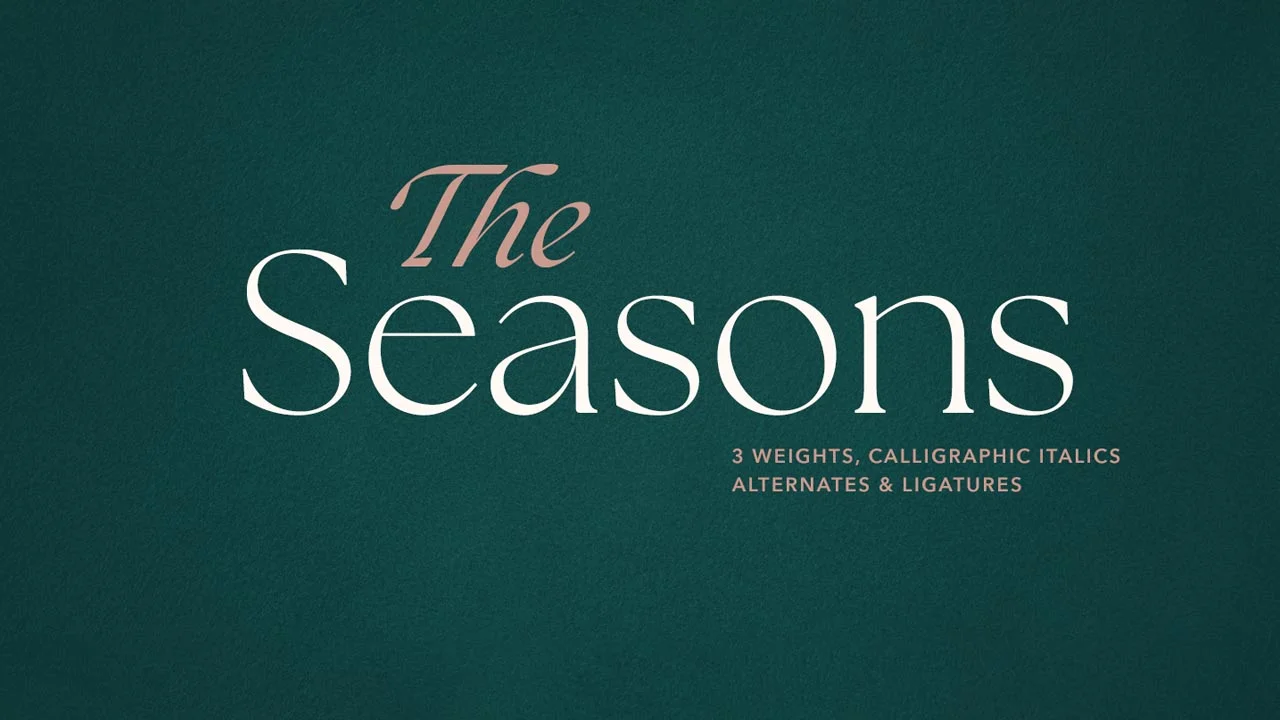
✅ Phù hợp: Thiệp cưới, thương hiệu cao cấp, logo thời trang
✅ Ưu điểm: Nét thanh thoát, uốn lượn tinh tế, mang lại cảm giác quý phái
2. Hello Valentine – Font Lãng Mạn
✅ Phù hợp: Thiết kế Valentine, quảng cáo sản phẩm nữ tính, blog cá nhân
✅ Ưu điểm: Nét mềm mại, chữ nghiêng nhẹ nhàng, tạo cảm giác ngọt ngào
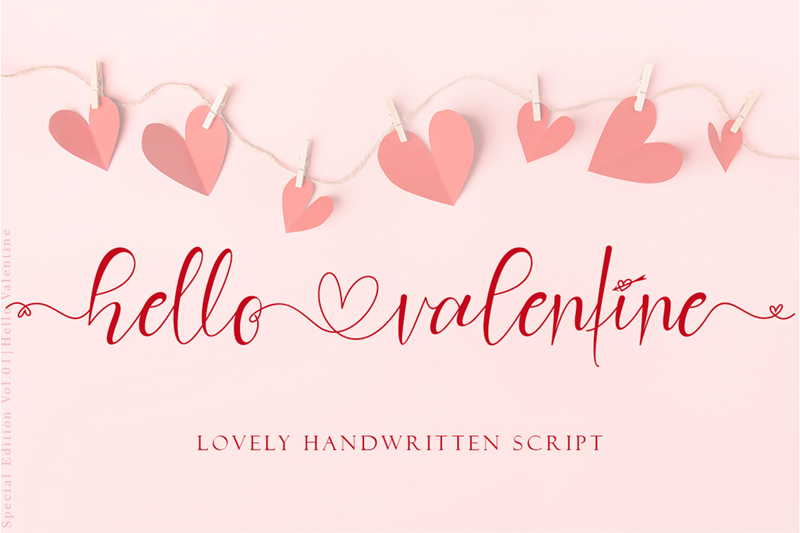
3. Brusher – Font Viết Tay Phóng Khoáng
✅ Phù hợp: Poster nghệ thuật, cover album, thiết kế sáng tạo
✅ Ưu điểm: Nét bút lông đậm, phong cách tự do, phù hợp thiết kế cá tính
4. Sweetie – Font Dễ Thương Cho Thiết Kế Trẻ Em
✅ Phù hợp: Bao bì kẹo, sách thiếu nhi, quảng cáo đồ ngọt
✅ Ưu điểm: Nét tròn trịa, đáng yêu, tạo cảm giác vui tươi
5. Magnolia Sky – Font Viết Tay Vintage
✅ Phù hợp: Logo quán café, nhãn rượu, thiết kế retro
✅ Ưu điểm: Phong cách cổ điển, nét thanh đậm rõ ràng
6. Autumn Leaves – Font Mùa Thu Lãng Mạn
✅ Phù hợp: Thiệp mời, bìa sách, thiết kế mùa thu
✅ Ưu điểm: Nét bay bổng, phù hợp phong cách thơ mộng
7. Pacifico – Font Viết Tay Phổ Biến
✅ Phù hợp: Logo, slogan, thiết kế biển hiệu
✅ Ưu điểm: Dễ đọc, nét mượt mà, tương thích nhiều nền tảng
8. Rochester – Font Viết Tay Thanh Lịch
✅ Phù hợp: Chữ ký, thiệp cưới, thư pháp Tây
✅ Ưu điểm: Nét mảnh, sang trọng, phù hợp in ấn cao cấp
9. Black Jack – Font Viết Tay Cá Tính
✅ Phù hợp: Thiết kế nam tính, thương hiệu thời trang, tattoo
✅ Ưu điểm: Nét đậm, phóng khoáng, phong cách street-style
10. Dancing Script – Font Viết Tay Mềm Mại
✅ Phù hợp: Website, thiệp mời, quảng cáo nhẹ nhàng
✅ Ưu điểm: Chữ nghiêng tự nhiên, dễ sử dụng
Lời Khuyên Khi Chọn Font Viết Tay
✔ Logo & Thương hiệu: Chọn font có nét độc đáo như The Seasons, Brusher.
✔ Thiệp cưới & Sự kiện: Ưu tiên font lãng mạn như Hello Valentine, Magnolia Sky.
✔ Quảng cáo & Bao bì: Dùng font dễ đọc, bắt mắt như Sweetie, Pacifico.